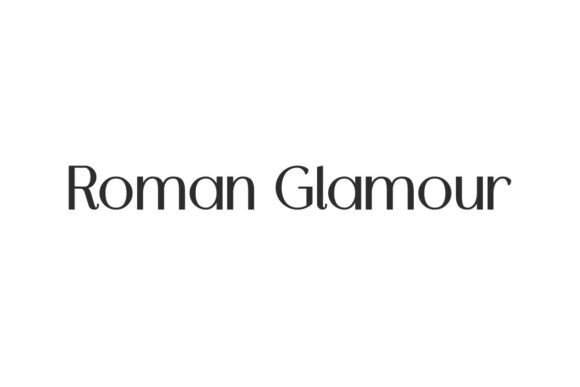
Roman Glamour
Roman Glamour: Uma Fonte Sans Serif Luxuosa e Multifuncional
A Roman Glamour chega ao mercado como uma fonte sans serif que combina elegância minimalista com alta legibilidade. Desenvolvida para atender a projetos que exigem um toque premium sem exageros, ela se destaca em diversas aplicações — de identidade visual a embalagens de produto.
- Design elegante e clean – linhas suaves que dão um ar sofisticado a títulos, cabeçalhos e logotipos.
- Versatilidade total – funciona perfeitamente em anúncios, apps, cartões de visita, sinalização corporativa, convites, rótulos, pôsteres, camisetas, embalagens e muito mais.
- Conjunto completo de caracteres – inclui maiúsculas, minúsculas, números, pontuação e símbolos.
- Suporte multilíngue – inclui caracteres latinos estendidos, facilitando o uso em português, espanhol, francês, alemão, entre outros.
Por que Roman Glamour é a Escolha Ideal para Seu Negócio?
Se você atua em segmentos como beauty clinic, bolsa de noiva, moda, artesanato, maquiagem, skin care ou spa, a Roman Glamour transmite imediatamente a sensação de qualidade e confiança. Seu aspecto “premium mas simples” cria uma identidade visual que se destaca tanto em mídias digitais quanto em materiais impressos.
Aplicações Práticas
- Logotipos de marcas de moda e beleza
- Cartões de visita e papelaria corporativa
- Títulos de sites e aplicativos
- Convites de casamento e eventos especiais
- Embalagens de cosméticos e produtos de luxo
- Posters, flyers e anúncios publicitários
- Design de camisetas e merchandise